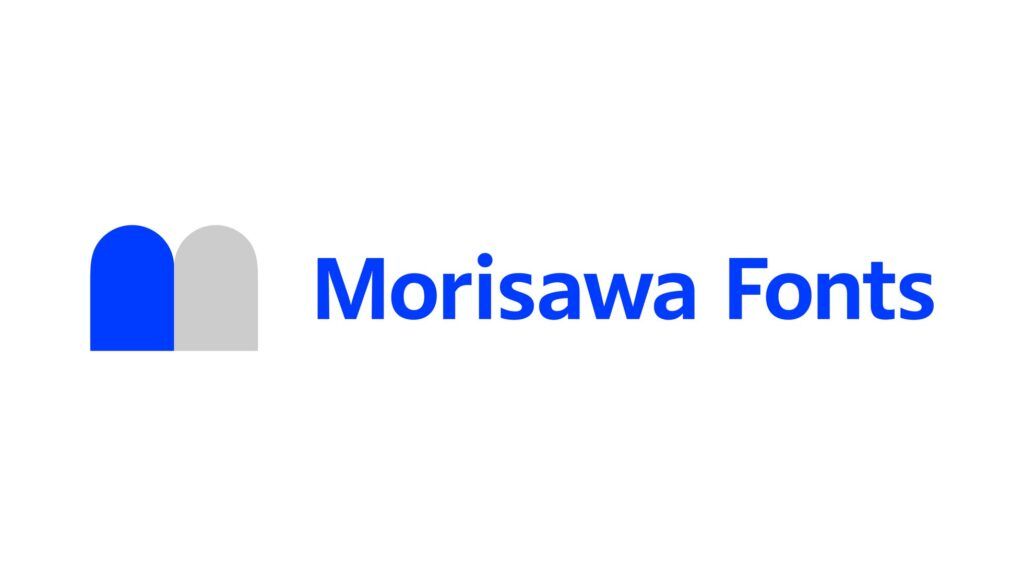
モリサワ 2,000書体以上のフォントライブラリーを導入できる「Morisawa Fonts 教育機関/公共団体プラン」提供開始 プロ仕様のフォントが気軽に使えて将来に役立つ
株式会社モリサワは、2,000書体以上のフォントライブラリーを導入できる「Morisawa Fonts 教育機関/公共団体プラン」の提供を開始した。
「Morisawa Fonts 教育機関/公共団体プラン」の「設備ライセンス」では、教育機関および公共団体が管理する共有の設備PCにフォントを導入できる。
教育現場における充実したフォント環境が実現するほか、ユニバーサルデザインフォントをはじめ高い可読性と視認性を備えたモリサワのフォントが、公共団体の広報紙や案内表示などさまざまな情報伝達を支援する。
さらに「Morisawa Fonts 教育機関プラン」には、学生が制作で利用する個人PCや、教職員が学生指導や研究で利用する個人PCのフォントライセンスを教育機関が一括管理できる「包括ライセンス」も用意している。学生はプロ仕様のフォントが気軽に使えることで、学びをより深めるとともに将来の職業や進路選択にも役立てられるほか、教職員も教材や配布資料のクオリティーが向上する。また、教育機関全体でフォントを整備することで、学生の入学・在学の満足度や効果的な学習にもつながる。